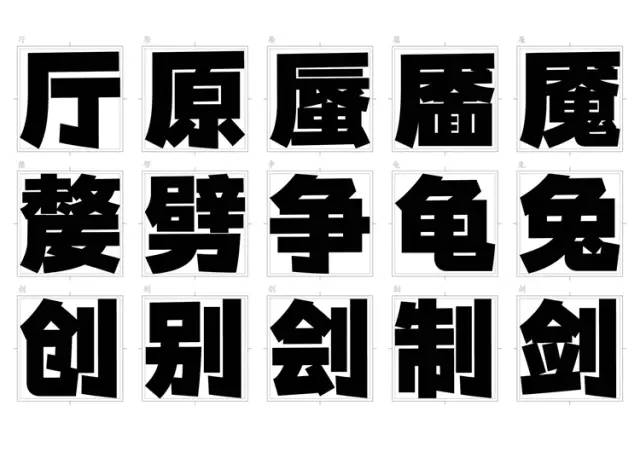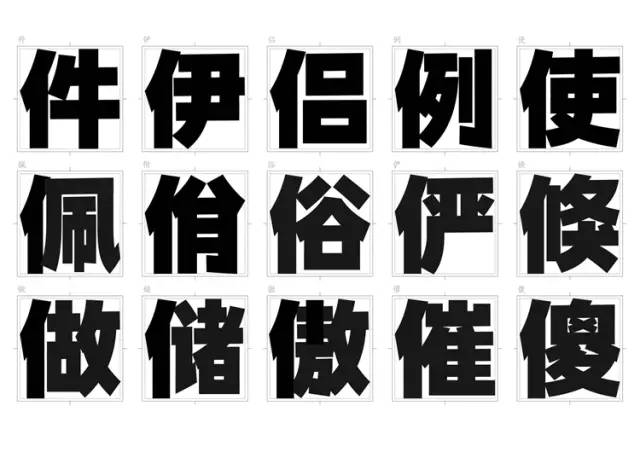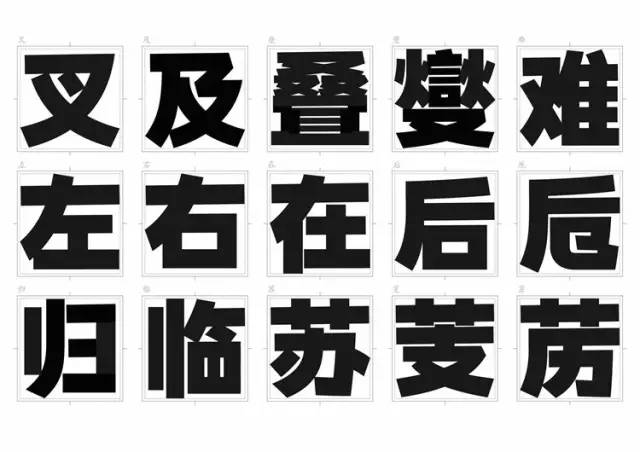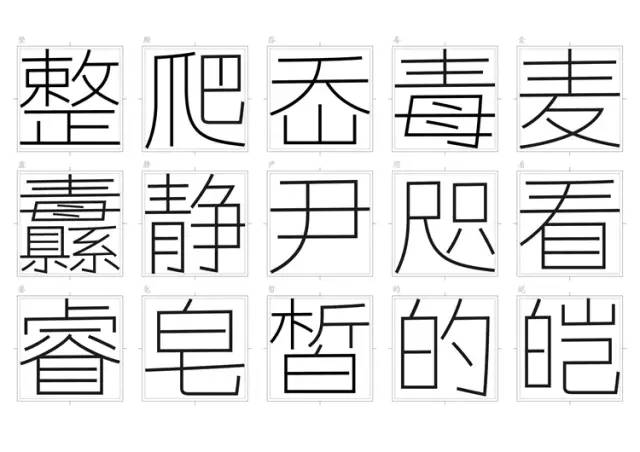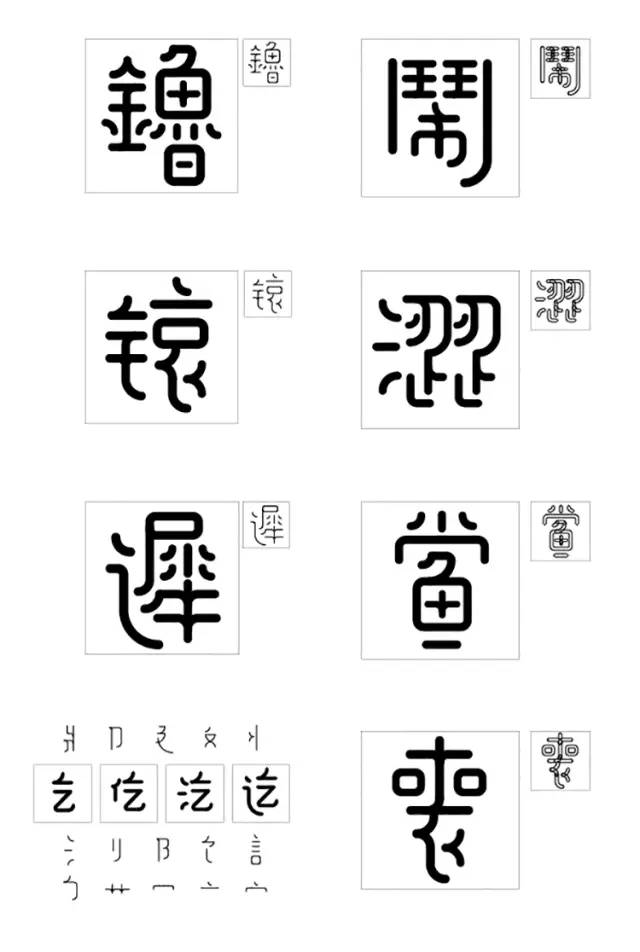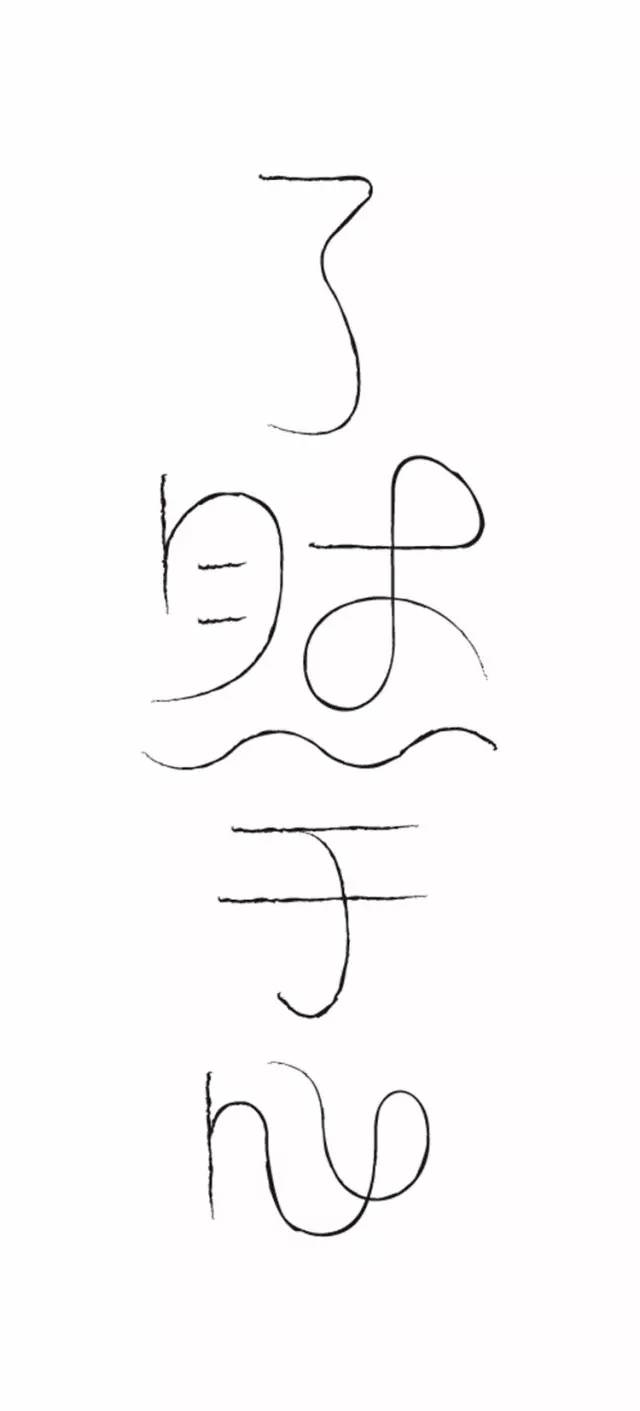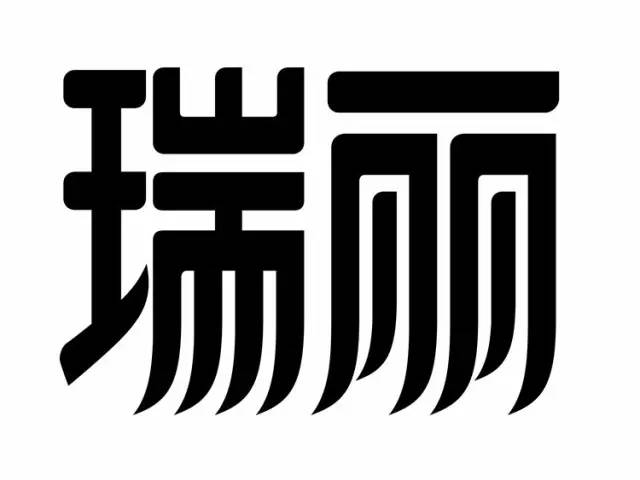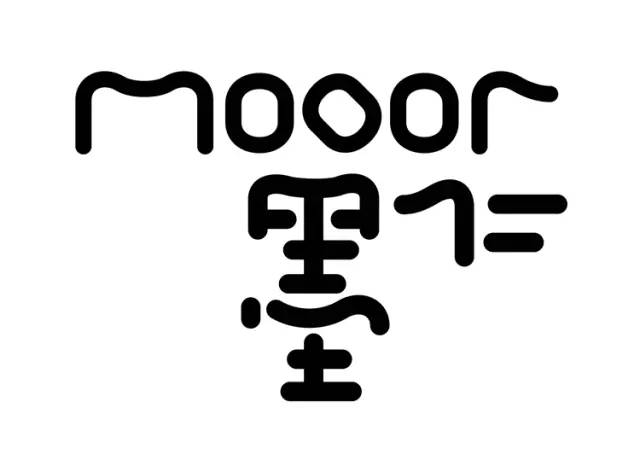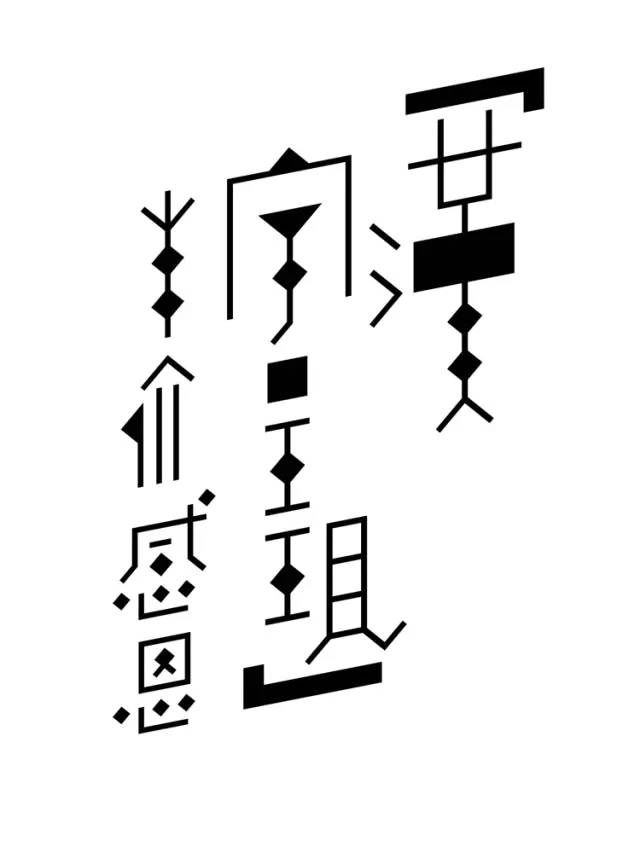
设计师的奢侈品——字型
岳昕
1981年就读中央工艺美术学院(现清华大学美术学院)装潢系 书籍艺术专业1985年留校任教。先后在装潢系和基础部执教2003年至今 元隆雅图文化传播股份有限公司艺术总监清华大学美术学院/北京服装学院外聘教师
我看字体设计
近30年来,全国性的汉字字体设计热潮有过三、四次,最近的这次似乎要比以往更持久。虽然只是短时的热潮,但每一次在“字体热”的温度褪去后还是会留下一些好的字型,也会涌现些字体设计新人。多次“热潮”不断推动着汉字字体设计的进步和发展。
对于字体设计,人们有不同的概念界定,对于字体设计师也有多种身份的划分,但这些并不重要,因为字体设计热潮带来的更加丰富的字体和被逐渐总结提炼的字体设计方法以及系统理论的完善才是大家的核心关切。
严格地说,由于性质独特,汉字字体设计是独立于平面设计、图案设计和传统书法之外的独立设计类别。字体设计包含了现代艺术、传统书法、绘画、图案装饰和终端技术等综合因素,是经过艺术加工、设计处理和图形装饰的实用类字型
直至清末,西方的铅字排版印刷术才传入中国,才使得汉字字体设计进入铅字时代。 1909年,诞生了中国第一套楷书印刷字体,它具有浓郁的汉字书法神韵。1916年,杭州西泠的丁辅之等人为商务印书馆刻制了“仿宋体”,全新的字体兼备宋体和楷体的神韵,挺拔秀丽。随后,根据拉丁字体中的等线体创制的具有现代风格的黑体字也传入中国。至上世纪三四十年代,仿宋、黑体、楷体等现代最通行的印刷字体先后出现。
直到1960年代,现代汉字字型创造(字库字体)才被真正归为设计范畴,在此之前汉字字型处理工作仅限于对于传统手工刻本字型和购买的用于铅印的金属字模的临摹、修补、派生和延展,其方式也仅限于工匠、作坊式的师傅带徒弟,经验散碎,匮乏理论。之后,由于印刷技术的发展和拉丁字体设计思潮的影响以及现代艺术、装饰、构成等因素的介入,出现了以传统书法和活版刻本为技术依托,具有一定规模的现代汉字字体设计专业机构,开始了真正意义上的字体设计,而这已经是1960年代以后的事了。
我认为好的设计
我认为好设计(平面设计和字体设计),首先是好看,赏心悦目,这是最基本的条件。创造“美”和“悦目”是设计师的天职。其次,好的设计应该具有通过视觉梳理,传达有序信息的能力。最后,好的设计没有时代阈限,永不会过时。
字体亦然。
字型要悦目,编排易读,如老宋体、仿宋体和黑体般经久耐看。但是,字型好看仅仅是成功的第一步,衡量一款字型优劣的标准是常被人们忽略的排版应用的阅读感受,这才是判定字型是否成功的终极标准。
我的字库字体设计
没有一模一样的字体,也不应该有固定的、程式化的设计方法和模式(相反,方法和模式对于设计师来说是不幸的灾难)。我的设计没有固定方法和模式。
由于不善书法,在我眼中汉字字型就是一个个奇妙、莫测的图形。设计汉字字型如同在方格中布局不同形状的细碎图形(笔形),遵循图形、图案的均衡、对称、疏密、开合、方圆等形式法则,在字格中随意或松散、或紧凑、或上浮、或下沉。当然汉字字体设计并非仅限于此,这样制定系统规则并不能涵盖汉字造型的全部,汉字字体的“精”、“气”、“神”和生命力产生于汉字独有的形态特征中,是最不容易认识和把控的,如:汉字的“势”、“态”和“面背”等因素是图形、图案法则之外的,但对于汉字字型设计而言却是不可或缺的关键因素。其中“面背”特指字型的方向性,它跨越了图形图案的“对称”和“均衡”问题,具有强烈的主观拟人特性。如:“欠”、“万”、“佳”、“包”等字为左背右面,“寸”、“气”、“匀”、“子”等字为左面右背,“面背”现象普遍存在于汉字之中 。
抛开书法,我认为汉字字体设计分为两部分:字库字体和组合字体。近年来产生的“实验字体”大都依托海报、卡片、书籍杂志版面编排和数字终端为呈现介质和表现目的,重点并非字体本身,更准确的称呼应该是以汉字为元素的海报设计、版面甚至是装置和公共艺术设计。因此我认为它们不应属于字体设计范畴。
“字库字体”的设计目的是为标题、正文、注释、表格等设计相应和适合的字型。目前,字数数量依字库规模不同分为:6763个、8877个、9169个、27533个直至超大字库的70244个。
“组合字体”是将所要设计的“词”、“句”的文本内容充分表现和将“词”、“句”的若干个字组织在预先规划的组合架构之内建立崭新字体组合形态的双重目的的设计。字库字体字型的关键是完整统一和识别性。组合字体的核心是巧妙的内容表达和字型的创新组合。
设计动机不是源于显而易见的笔形特征,而是建立在对于结构形态的发现和创新的基础之上。我认为间架结构是汉字字型的核心和关键。如:《博雅宋》、《旗黑》系列,它们好看易用的关键在于字体的间架结构,在于字型的清晰、疏朗、端正和排列的相对齐整性。
去年汉仪字库出品的《元隆黑体》,就是我在字型结构上思考和酝酿的结果。这个思考用了28年时间。元隆黑体诠释了我的审美哲学和设计价值观:朴素、松弛、慵懒、平稳、瞻前顾后和不动声色。字型间架结构外紧内松、空白均匀、重心低稳、字面宽大、张力外扩。“外紧内松”使得字面扩张,结构松弛,减小排版字据,利于长时间阅读。“空白均匀”是元隆黑体间架结构系统的核心,空白均匀是为了清晰表现每个笔形的形状和形态。笔形明确,结构就会清晰,清晰的结构自然疏朗和通透。“重心低稳”的单字虽不显洒脱,却是推迟阅读疲劳的最佳手段。
- 元隆粗黑体 -
- 元隆纤黑体 -
- 元隆黑体结构特征 -
之后我设计了《六字黑体》,对我来说堪称一次“凶险”的自我挑战。整个过程与其说是写字,不如说是一场永无尽头的拼图游戏,与规范庄重的《元隆黑体》形成鲜明的字型对照。看似字体最突出的部分是奇特、有趣的笔形塑造,其实结构设定才是重中之重。笔形造型规范用去三天时间,而结构系统的设定却用了两个月之久。既严谨又随性的结构规律源自我长期从事图形和标志的设计心得和构成标准。全部6763个字都是以设计图形标志的标准和方式处理和加工。模块式的笔形衔接方式和固定的笔形单位造就了《六字黑体》独有的、不可复制的拼图式间架结构秩序,笔形与笔形之间既有险要和灵动,也有坚实和平稳。机械单纯的笔形游动在特定的间架结构的限制之中,呈现出丰富多彩的图形拼接式样,也流露出了我对未来汉字字体设计方向的思考。
- 六字黑体 -
《六字黑体》的结构剖析:
1. 笔形和空间的基础单位为正方形
2. 模块式组装形式
3. 以“基础单位”为组合搭接标准
4. 触碰式搭接突破汉字图形化的表现局限
- 六字黑体结构剖析 -
《新月体》是我刚刚设计了4000个字的新字体,它的结构关系还没有最终确定。原字稿是我2015年获得腾祥字库字体比赛的优秀奖作品。对于汉字的美,人们有着不同的理解和阐释,这些“不同”使汉字的美得到了充分的诠释和丰富的设计表现。
汉字美的核心是什么?
如何触到汉字美的灵魂?
怎样的字形才能够准确揭示汉字之美?
我希望以这款字型的设计可以作为多年来对于这些问题思考的答案。设计初期,制定了尽可能彰显汉字具有的绘画特征的结构规范,设置了突出汉字的图形、图案化因素的统一归纳规则,强调了汉字的“对称”、“镜像”、“重复”、“呼应”和“诙谐”的本应属于图形图案设计的形式法则。这款字体的图案化因素在已有字库字体中是罕见的。
我始终认为笔形问题是局部问题,小问题。
- 新月体 -
- 新月体结构分析 -
我的组合字体设计
面对 “词”、“句”的内涵表现和“词”、“句”字型的组合,我习惯把注意力放在后面的组合工作上。我深信组合字体内容的表现依赖于字体本身结构和笔形关系呈现出的视觉语言来表达 ,是作用于人们的内心深处,绝不是简单表象的“符号标注”。在组合字体中植入图片、图形我认为是危险的尝试。加入具体写实形象的同时,人们无意间减弱了字型本身对于内容的更加深层和高级的表现力,使组合字体流于表面的象形而变得庸俗。从更加严格的意义上说,这也不应该属于字体设计范畴(文本内容是由图形和图案表现的)。当然,处理巧妙的图形组合字体,完全可以达到大俗大雅的崇高境界,但案例罕见。
“组合”处理的崇高境界是:无法之法,率性而为。它的必要前提是熟悉将要“组合”的这几个字的结构特征和“部件”,剖析字的结构关系,超越单字概念,探索扩展结构组合的可能性,视多字为一体,捕捉内在的视觉因素和系统 ,即:
1. 梳理共性——发现隐藏在字里行间可利用的元素,提取汉字笔画中的存在的重复、对称、旋转、镜像等图形、图案设计形式法则的潜在基础元素。依据文本内容的需要选择应用最为恰当的元素进行设计。
2. 洞察玄机——排除习惯性的观察单字形与分解笔画的习惯,从完整的组字(或完整图形)角度观察组合字体,以字当画,运用绘画的思维方式,排列处理汉字,为后面的设计埋下伏笔,创造机会。
3. 把控细微——细部的表现力取决于位置的选择和数量的控制。“画龙点睛”、“四两拨千斤”恰是对组合字体细微小笔形绽放光彩,释放能量的准确概括。通常不会恰巧遇到数量适合的微小笔形,它们的数量提取和恰当组织尤其是位置的“布设”是对设计师能力和智慧的严峻考验。
4. 布设奇妙——在原本并不具备连带关系的零散元素中“制造”形与形,形与空间可能形成的有机关系和相互作用,以及呼应的可能性。“无中生有”便是为构建组合整体架构而主观增加和重复原有字形基础中不存在的笔画和元素。
5. 视而不见——尽量缩小、弱化与总体节奏不和谐及妨碍统一因素或为设计的简繁而作的元素遮挡、省略和替代。
6. 节外生枝——运用字型及笔划的形变提升设计的表现力,也是扩展词组文本内涵的绝妙方法。
《瑞丽》是典型的女士杂志品牌形象设计,没有花朵、丝带、红颜……,但两个字的均衡结构和洒脱笔形的塑造,尽显优雅与柔美。
《顺水云》是强调传承中国古代文化的互联网企业的“云服务”品牌形象,三个字的居中对称结构与篆书笔意笔形的处理,准确地描画出了一个立足中国市场的现代化企业服务平台的特有形象。
《墨仁》是高端治愈类文创品牌形象,不同于普通的滑稽和玩笑,通过自由随性,不拘章法的灵动架构,幽默诙谐、松懈拖沓的笔形表现了人们内心创伤治愈的活动过程和复杂心理。
《创意呈现》是著名设计网站古田路9号的设计年鉴封面字体方案。通过将汉字符号化处理和松散化排列,我极力表现当下时尚前卫的设计风。
《汉字呈现  半价感恩》是典型的设计快闪消费产物,因为“感恩活动”时限原因,字体设计用时20分钟,微信传播持续3小时。由于商家面对平面设计师,我采用繁体字进行几何图形化的处理,在迅速吸引设计师目光,激发设计师好奇心的同时,将“半价”活动和“字体”年鉴销售的信息直观表达。
总结
字型对于平面设计师来说是奢侈品,平面设计师具备如下素质才有可能关注到庞大字库系统中的细微——字型:
一.感觉敏锐
二.超强审美
三. 严苛标准
四. 精致细微
五. 思维缜密
平面设计师中自行调整、处理设计中所遇字型的人并不多见。他们着眼细微,强调统一、齐整,是设计师中的奢侈一族。